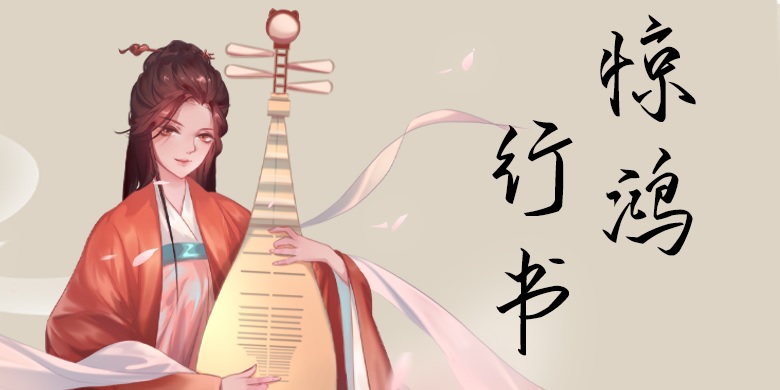
方正手迹-惊鸿行书
品牌:方正手迹设计师:余丹发行时间:2020字库编码:大陆简体(GB2312-80)分类:常规书写·硬笔字体属性:精品字
方正手迹-惊鸿行书
翩若惊鸿,宛若游龙。整体字形婉转优雅,起承转折,提按有度,风度翩翩,字如其名。适用于现代诗歌、短文排版,文化商业宣传,文艺类的书刊、品牌广告和产品包装设计,以及社交网络的个性化用字。